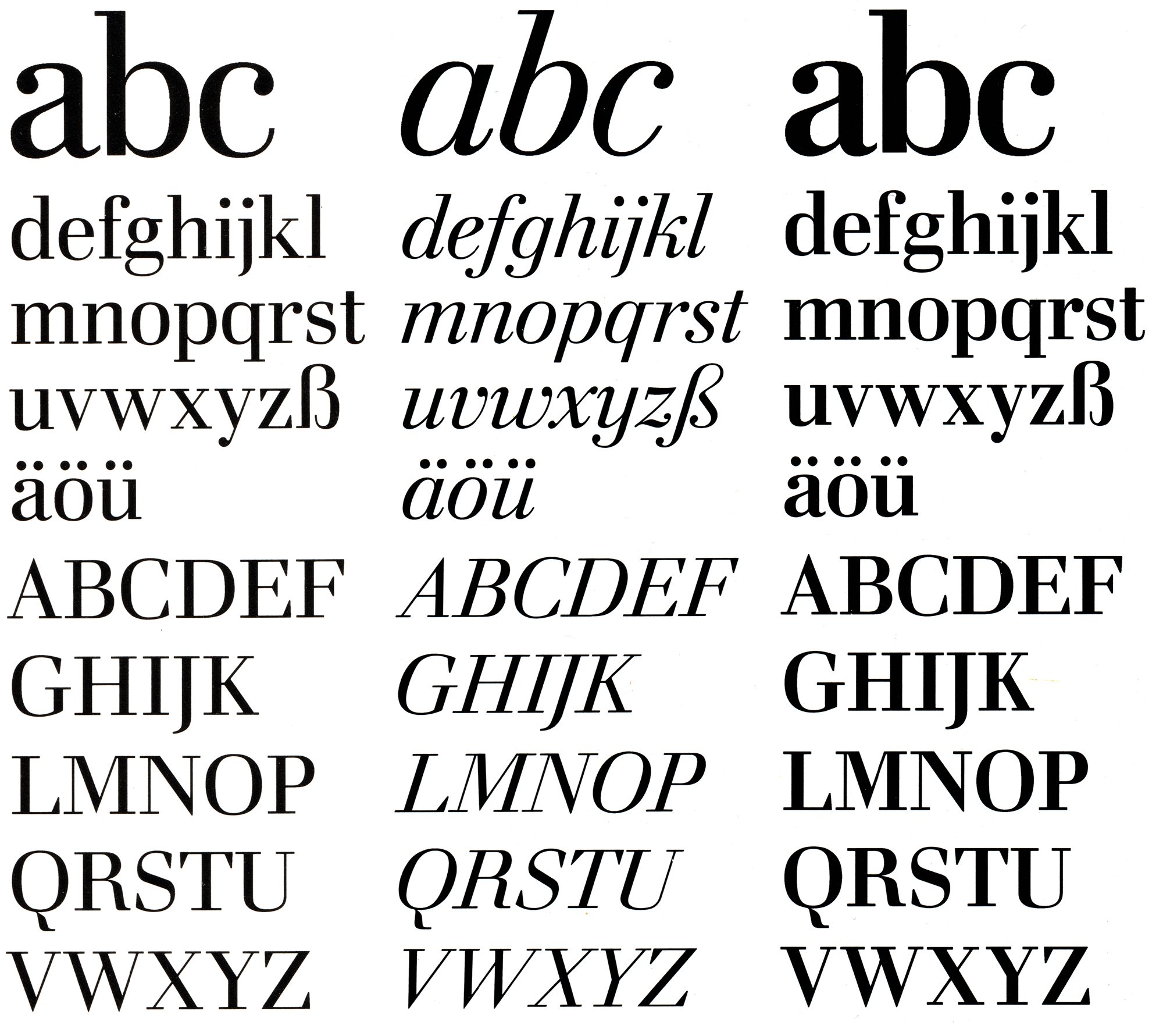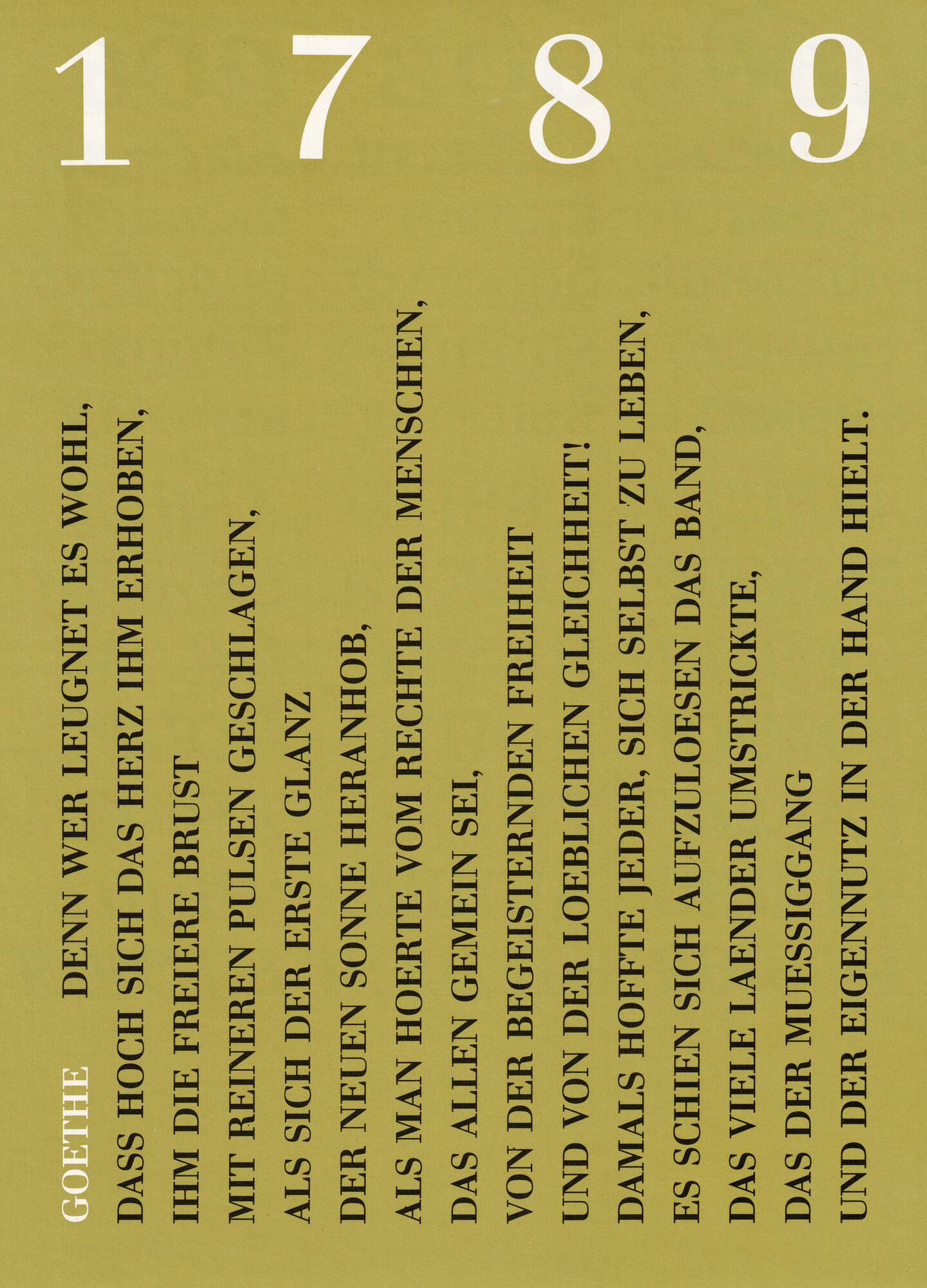
Die Prillwitz-Antiqua von Johann Carl Ludwig Prillwitz aus Jena entstand ursprünglich Ende des 18. Jahrhunderts als eine der ersten deutschen klassizistischen Schriften nach französischem Vorbild. Bei Typoart wurde die Schrift von Albert Kapr und Werner Schulze in den 1980er-Jahren für den Fotosatz neu bearbeitet. Verfügbar waren die Schnitte mager, kursiv und halbfett.
Elsner+Flake hat die Schriftfamilie auf Basis der Originalmaterialen in digitaler Form in zwei optischen Größen und mit erweiterter lateinischer Sprachabdeckung neu aufgelegt.